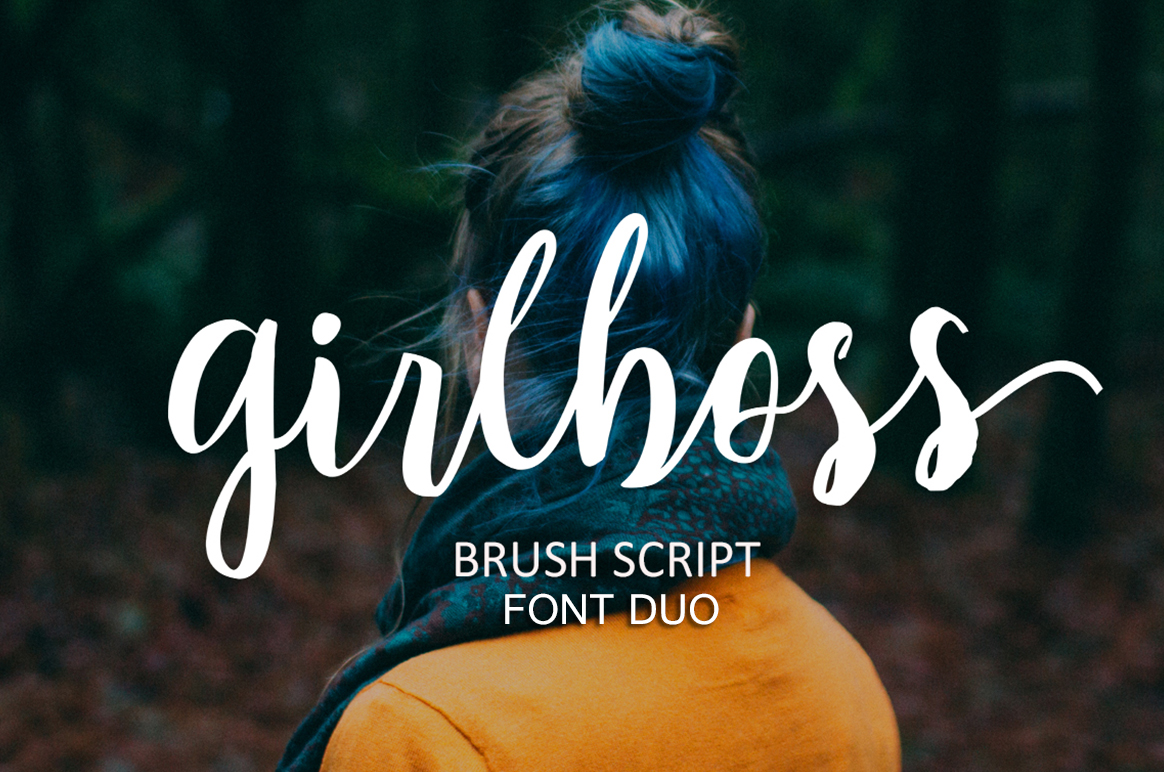
Girlboss Script
Nếu bạn đang tìm kiếm các tài nguyên chất lượng cao như Girlboss Script, gói cao cấp này là một lựa chọn tuyệt vời cho các dự án sáng tạo của bạn.
Được chế tác với độ chính xác cao, Girlboss Script cung cấp các vector sạch, kiểu chữ mượt mà và giấy phép thương mại để bạn yên tâm.
Cho dù bạn đang tạo sản phẩm POD (In theo yêu cầu), thiệp mời đám cưới hay đồ họa mạng xã hội, Girlboss Script đều là một sự lựa chọn lý tưởng.